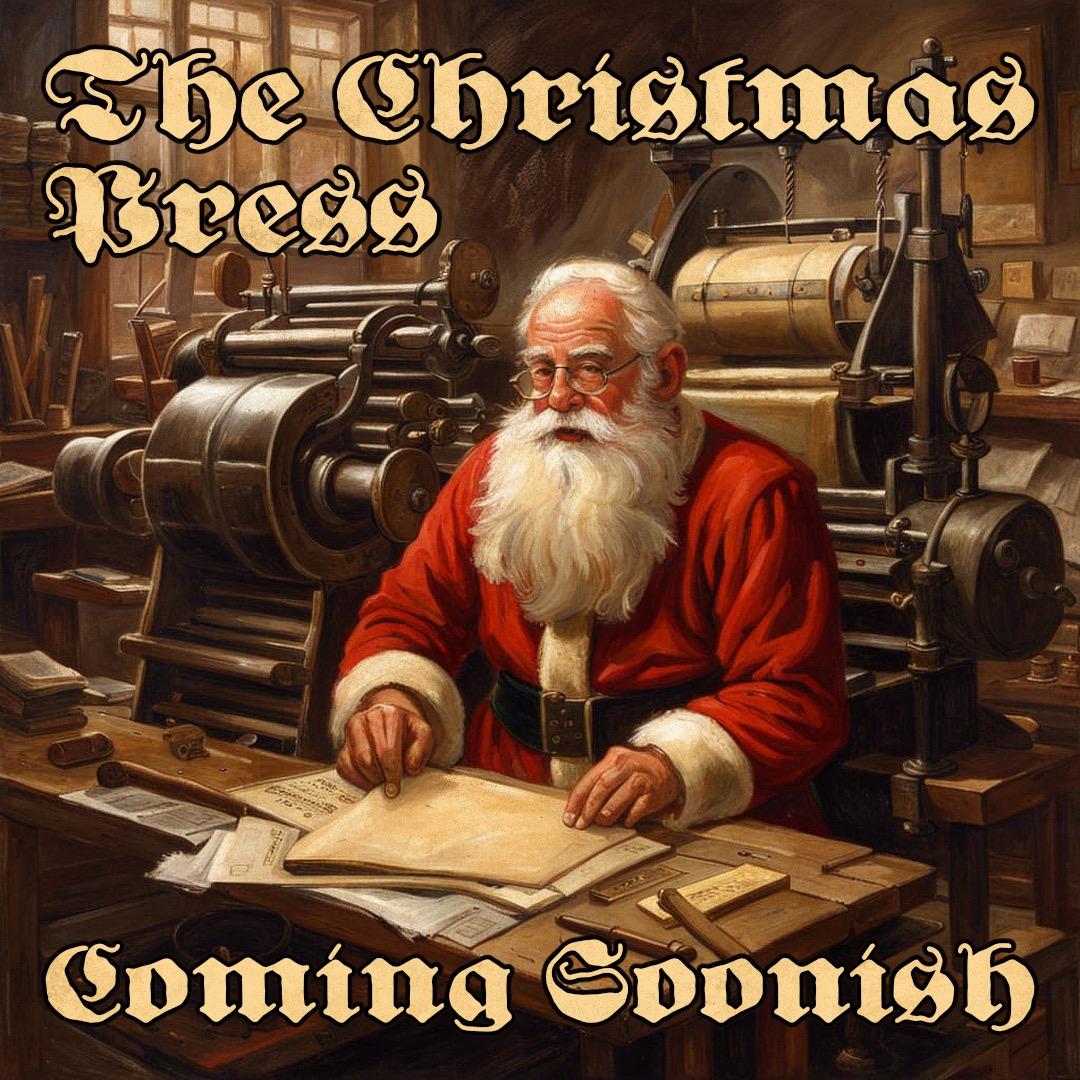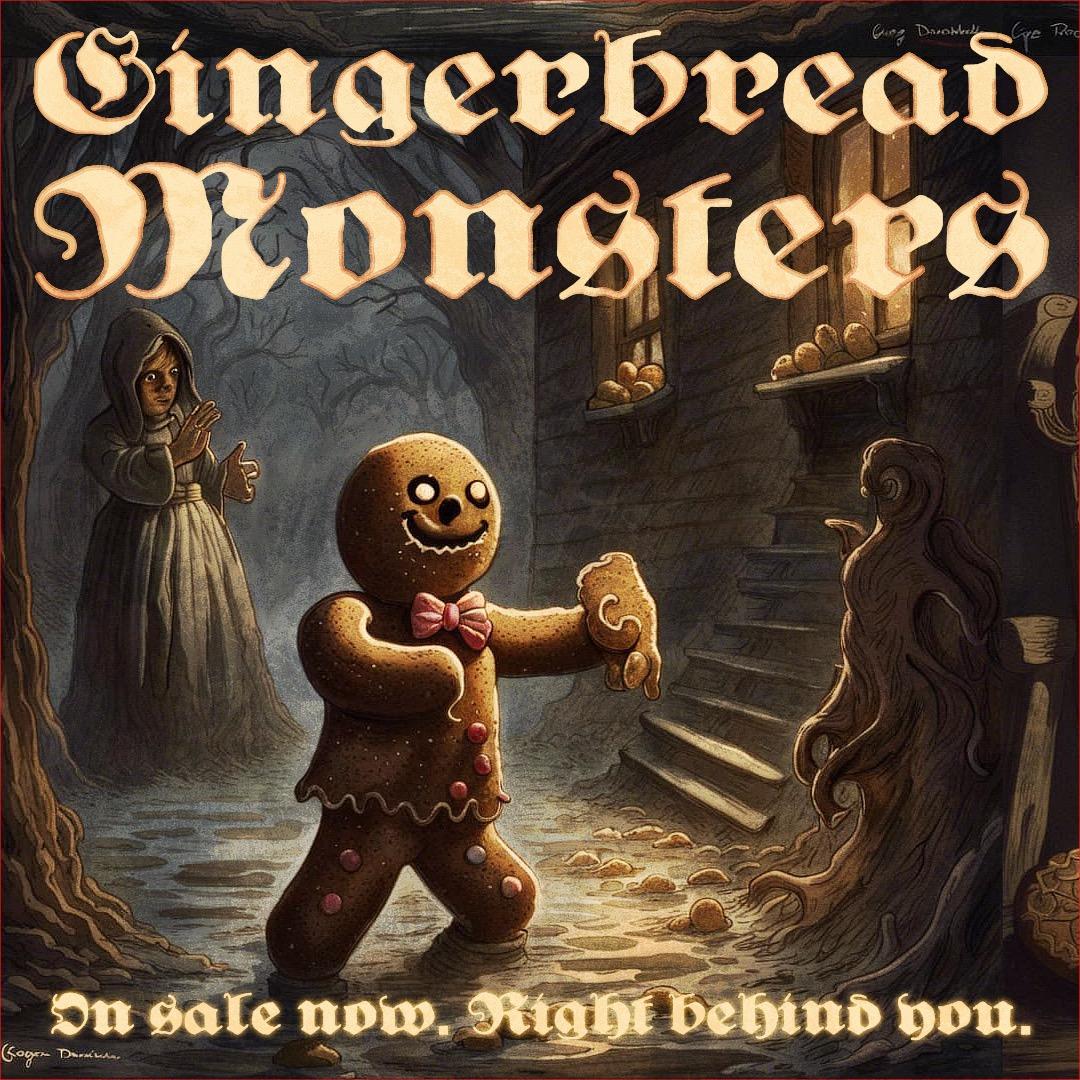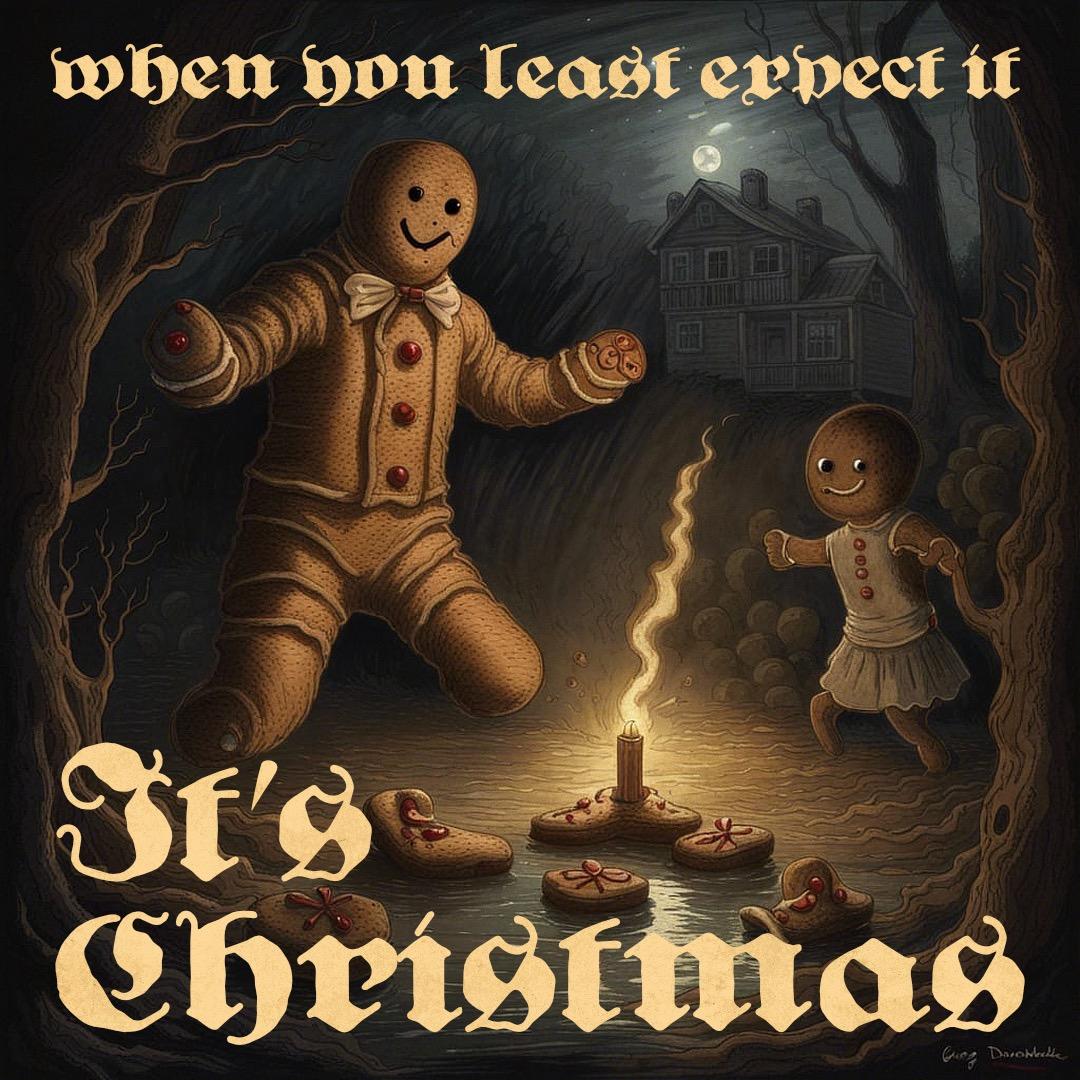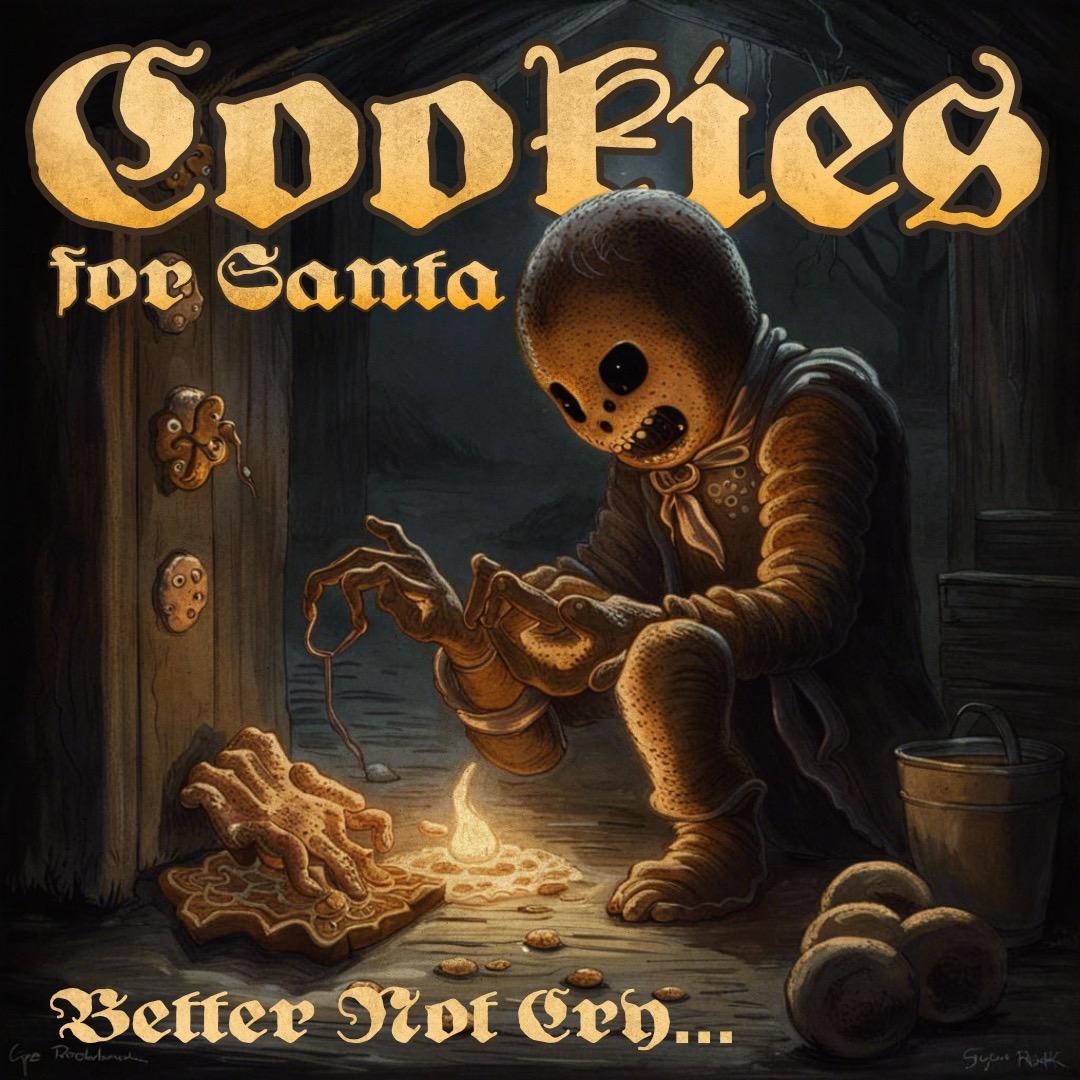
Weihnachtsschriften die vierte: fette Lehmann Fraktur
Ich war die letzten Monate total ausgebucht, aber jetzt schraube ich wieder an den Weihnachtsschriften herum. Dieser Kandidat ist die Fette Lehmann Fraktur. Fall jemand eine Probe hat, die W, X, Y und Z zeigt, würde ich mich über Bilder davon freuen.
Ich habe hier etwas mit einer AI experimentiert. Da gabs einen "Horror" Modus, den mußte ich gleich mal ausprobieren.
Vielleicht, vielleicht! Viel Fortschritt konnte ich bis jetzt auf keiner Front machen, und die magere ist doch arg gewöhnungsbedürftig.
Uiuiui. Ganz schön viel … öhm … Verschiedenes hier. Bin neugierig auf Deine »Christmas Press«, hast ja viel schönes Zeugs bei Walden Fonts. Wenn ich reich wäre, würde ich alles alles kaufen … nur um’s zu haben, und einfach für den Fall, dass ich mal auf Ideen komme.